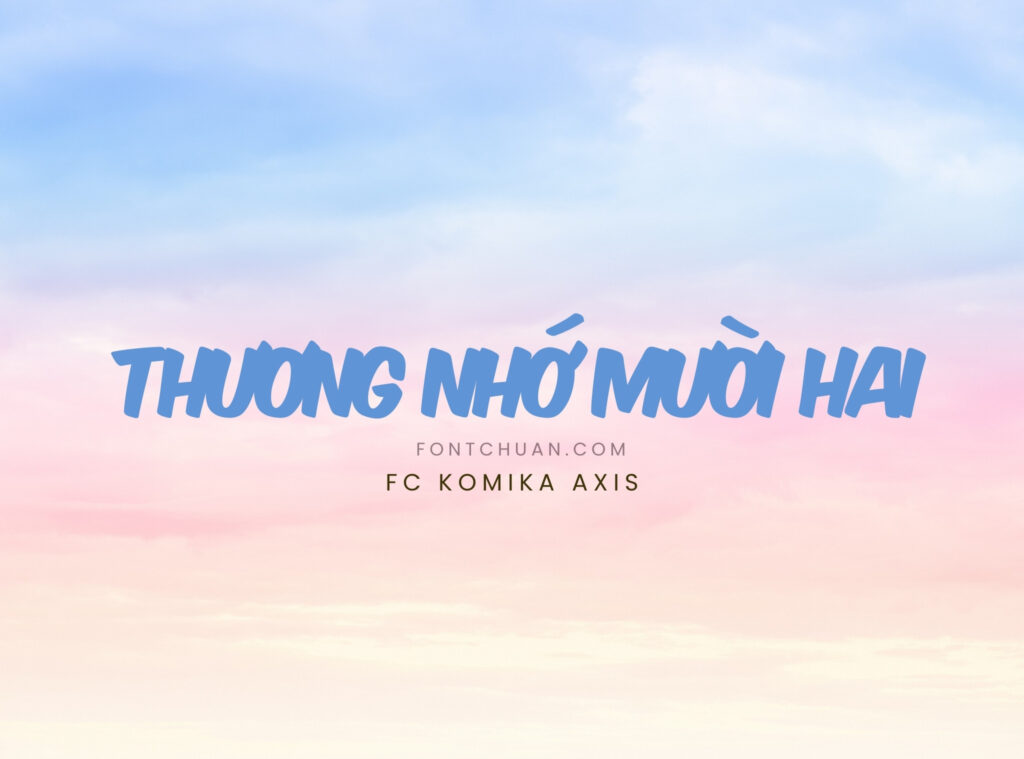
Komika là một họ phông chữ phong cách truyện tranh, được thiết kế bởi Apostrophic Labs. Phông chữ này mang đến cảm giác vui tươi và năng động, với các ký tự đậm và rõ ràng, phù hợp cho các dự án thiết kế như tiêu đề, poster, truyện tranh và các ấn phẩm dành cho trẻ em. Komika mặc định hỗ trợ đa ngôn ngữ, bao gồm cả tiếng Việt nhưng chưa tốt.
Ngoài ra, nhờ nét chữ đậm, tròn và sinh động, Komika cũng có thể được sử dụng như một Font chữ Halloween vui nhộn, mang đến không khí lễ hội tươi sáng, hài hước và khác biệt so với các font Halloween kinh dị truyền thống. Komika mặc định hỗ trợ đa ngôn ngữ, bao gồm cả tiếng Việt nhưng chưa tốt.
Về thiết kế, Komika sở hữu các đường nét mạnh mẽ, cấu trúc chữ cân đối và phong cách hiện đại, phù hợp cho nhiều mục đích sử dụng như thiết kế logo, tiêu đề, poster và các ấn phẩm quảng cáo khác. Ngoài ra, font này còn lý tưởng để áp dụng trong font chữ Tết như thiệp chúc mừng năm mới, banner trang trí Tết, font ngày nhà giáo Việt Nam cho thiệp, poster hay banner tri ân thầy cô, và font chữ Giáng Sinh trong các thiết kế thiệp, poster, quảng cáo mùa lễ hội, giúp các ấn phẩm trở nên sống động, vui tươi và thu hút sự chú ý.